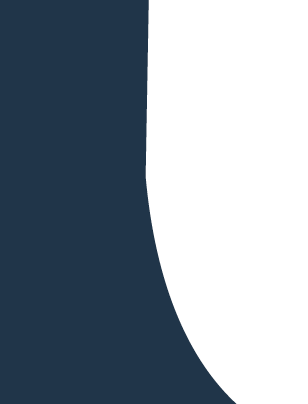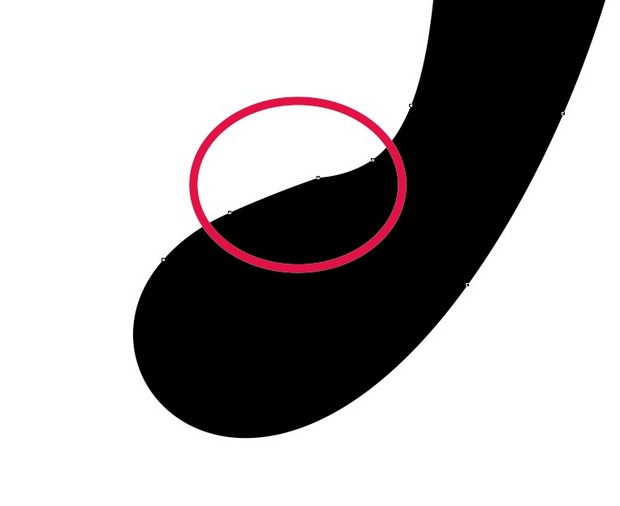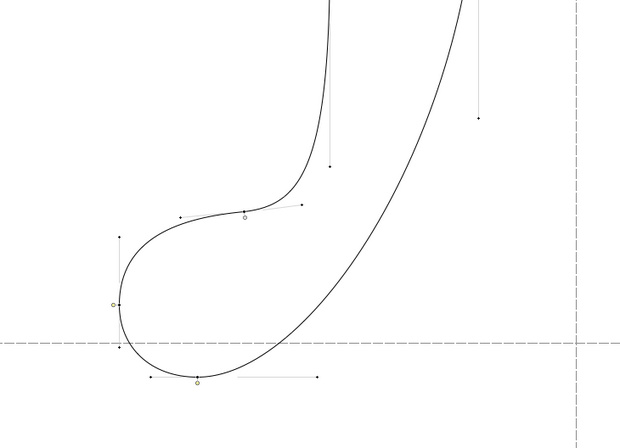
nur das kleine »h« ist leider missglückt. Sonst gefällt mir die »Joos« sehr gut.
Wenn man sucht, findet man noch mehr … a und d beispielsweise.
Ist aber trotzdem sehr hübsch, der gute :-P
habe mal den Buchstaben »d« in Kurven gewandelt. Konnte gefühlte 50 Prozent der Stützpunktknoten (ist das der richtige Begriff) löschen ohne dass sich die Kontur verändert.
Schrift ist wohl mit Illu oder Corel gemacht?
... oder sie wurde als Truetype gezeichnet und dann in Postscript gewandelt (oder umgekehrt).
Ich hab sie mal testweise für unsere Hochzeits-Einladungskarten eingesetzt. Einerseits ganz schön, andererseits schon wieder so speziell dass ich zweifle.
Ich hab sie mal testweise für unsere Hochzeits-Einladungskarten eingesetzt.
im Kontakt mit »typographies.fr« wegen »h« wurde mir geantwortet:
Wobei die Antwort so richtig ist?
I think there is a little confusion here :
Joos typeface was created in FontLab, and produced in .otf:
what happens if I open the .vfb or the .otf file in Fontlab ?
In fact I see none of the images you send me, I see this
(attached image).
Why is it different? I think it is because each software,
and each tool in each software, has a different way for
defining a line.
We think that, considering typography today, .otf may be
a very good way for defining a typeface, but if you "define"
this typeface in another software with another tool, this
software has to make the equivalent of a "translation" :
on complex design like Joos it generally adds points
for instance.
To conclude : if you can avoid vectorizing a typeface,
it is a good thing, if you have to, remember that the
software "does its best" but it does not mean it is perfect
and faithfull to the .otf file you have.
Last but not least, I do not think there will be any visible
difference between these three versions of "h" if we
consider them in a normal size for a letter (but be carefull
as some vectorization tools make the fonts bolder when
printed).
Man sieht in seinem Bild, dass die Anfasser nicht perfekt horizontal sind. Das ist nicht hundertprozentig optimal, aber auch nicht wirklich verboten. Bei der Bildschirmdarstellung kann das im Zweifel schon minimale Beulen verursachen – im Druck nicht. Von »missglückt« zu sprechen, wäre aber etwas übertrieben.